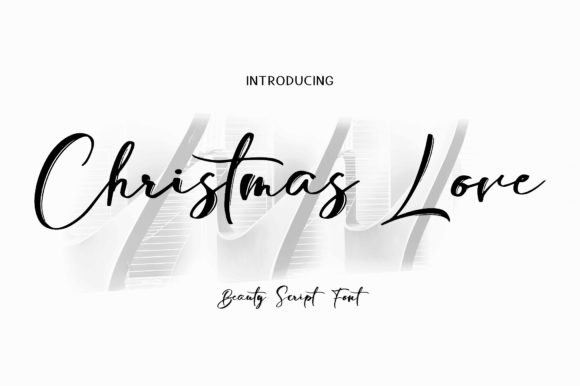
[Creativefabrica] Christmas Love Font (2021)
Christmas Love - это прекрасный и нежный шрифт, который излучает элегантность и класс.
Этот шрифт был создан специально для тех, кому нужен красивый и освежающий вид их дизайна.